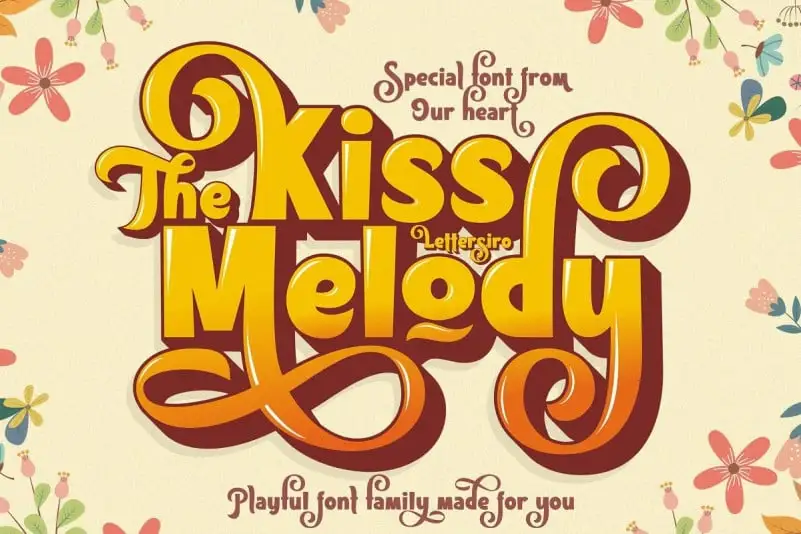
Kiss Melody Display Font – Download Grátis
Kiss Melody Display Font é uma tipografia sans-serif que captura a essência moderna inspirada nos últimos anos do Renascimento tardio. Suas linhas limpas e elegantes destacam-se com facilidade, especialmente quando utilizadas para projetos de grande escala como logotipos, posters, camisetas personalizadas, capas musicais, revistas ou qualquer outro formato visual exigente. Concebido pela Lettersiro, esta fonte foi criada para ser usada em formatos de exibição, onde suas características estilísticas alternativas e o set 09 estão disponíveis para criar um contraste interessante que não apenas aprimora a legibilidade, mas também adere perfeitamente ao tema musical ou artístico dos projetos. Seja você designer gráfico, editor de fotos ou criativo em qualquer outra disciplina visual, Kiss Melody Display Font é uma escolha inteligente para agregar um toque único e moderno a suas criações.